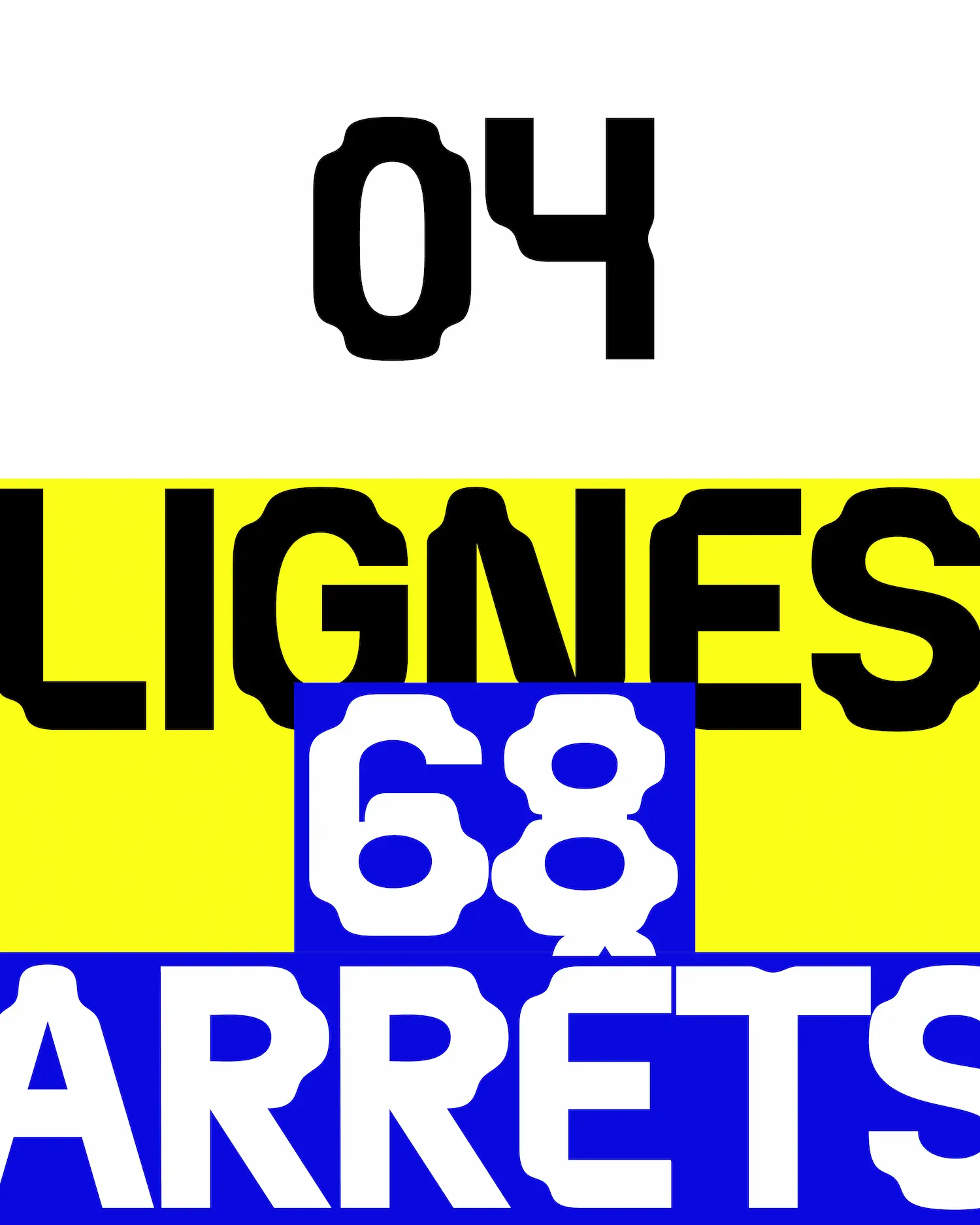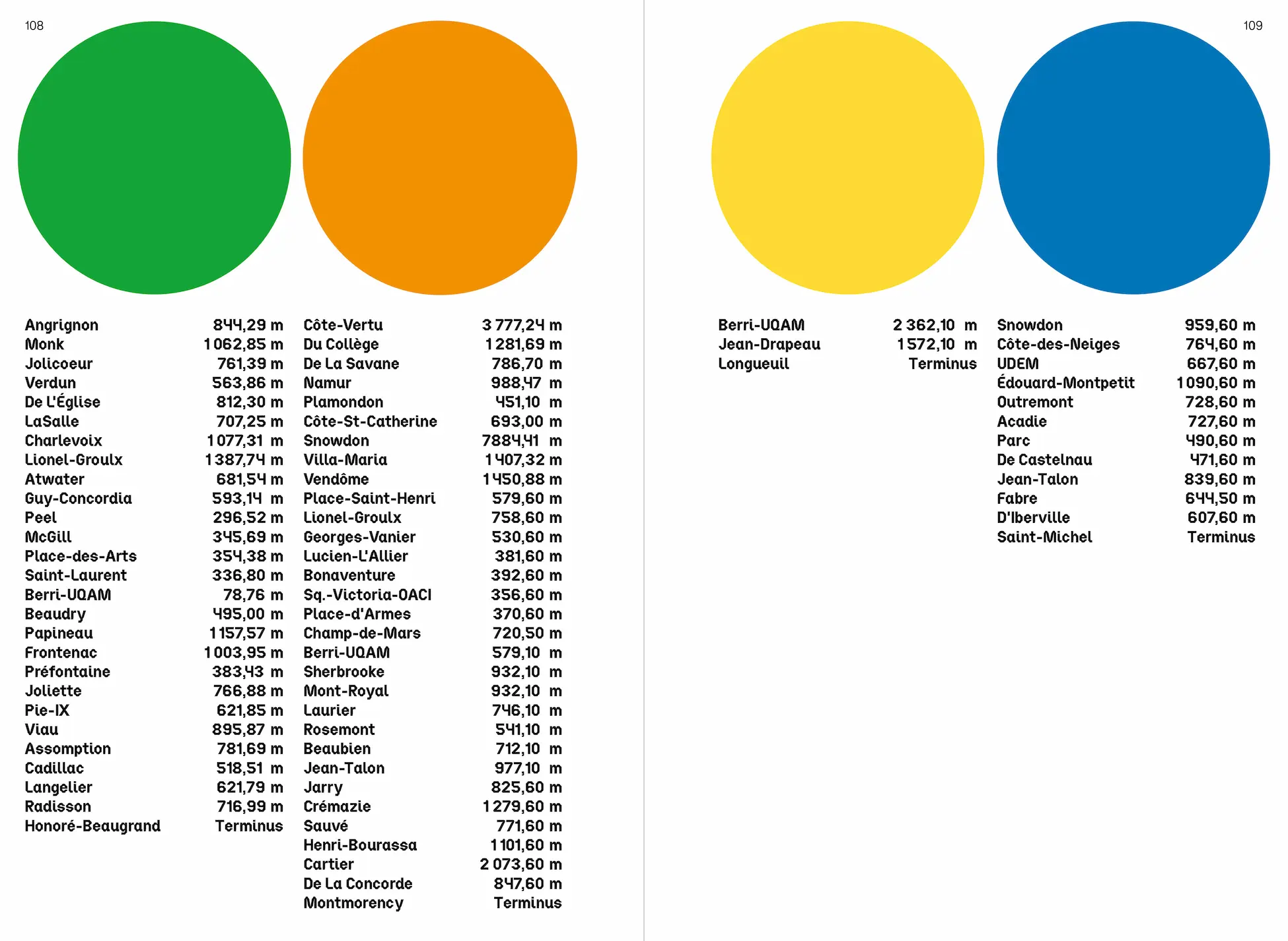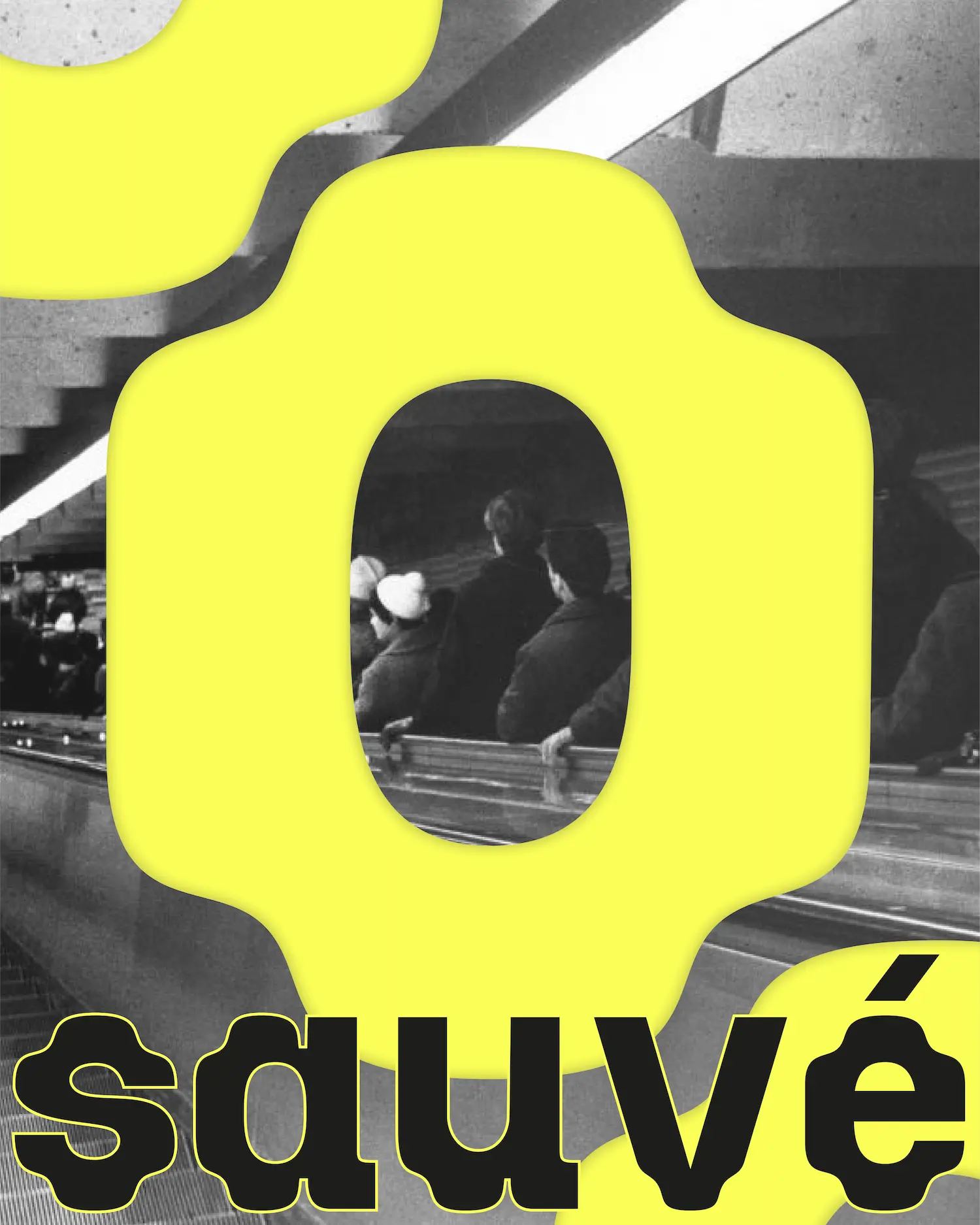
Prochaine Station
Cette police de caractères est née des 18 960 minutes (give or take) passées sur la ligne verte entre chez moi et le 1440, rue Sanguinet. Elle vient des 4 lignes et des 68 arrêts qui composent le métro de Montréal. Frontenac, Rosemont, Outremont, Peel, Sauvé… (j’ai nommé ta préférée ?). Les stations se succèdent, les mots passent sur l’écran rétroéclairé. Des lettres orange sur un fond noir, un ramassis de points qui nous mènent toujours (ou presque) à bon port. Ces compagnons du passager de l’heure de pointe sont toujours accompagnés d’une mélodieuse voix qui nous chante tous les jours : PROCHAINE STATION (.otf).